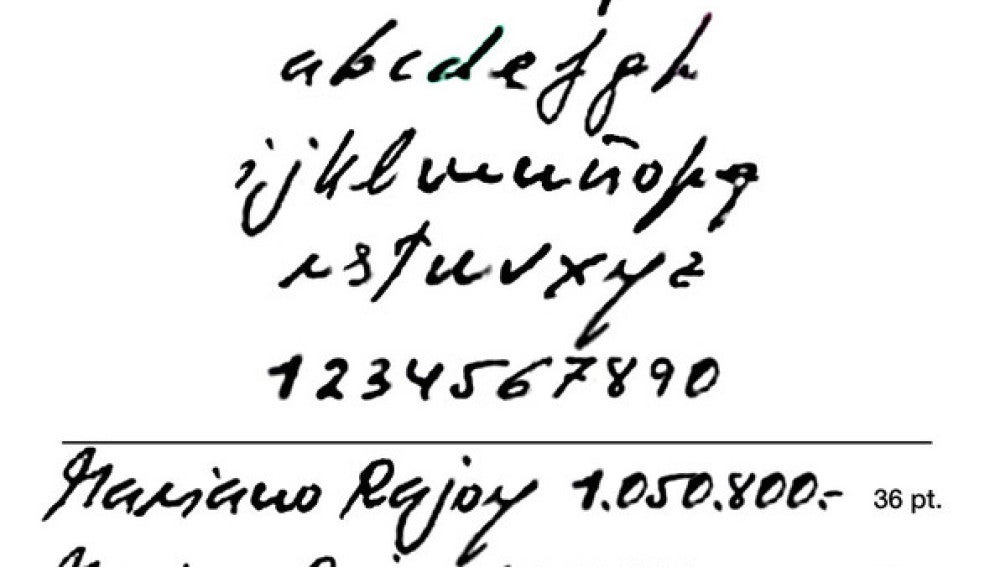
ESTA FUENTE HA SIDO DISEÑADA POR EL ESTUDIO IDENTYA
'Corrupt Script', una tipografía inspirada en los papeles de Bárcenas
El estudio Identya ha diseñado una tipografía inspirada en los papeles de Luis Bárcenas publicados por varios medios nacionales la semana pasada. Esta fuente ha sido nombrada 'Corrupt Script' y pretende reflejar el debate abierto sobre la autenticidad de las anotaciones presuntamente realizadas por el extesorero del PP.
Corrupt Script